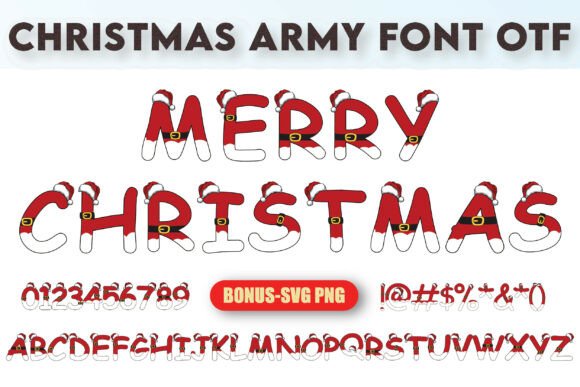
Christmas Santa
หากคุณกำลังมองหาเนื้อหาคุณภาพสูงเช่น Christmas Santa แพ็คเกจพรีเมียมนี้เป็นตัวเลือกที่ยอดเยี่ยมสำหรับโปรเจ็กต์สร้างสรรค์ของคุณ
สร้างขึ้นอย่างแม่นยำ Christmas Santa ให้เวกเตอร์ที่สะอาด พิมพ์ตัวอักษรที่ราบรื่น และใบอนุญาตเชิงพาณิชย์เพื่อความสบายใจ